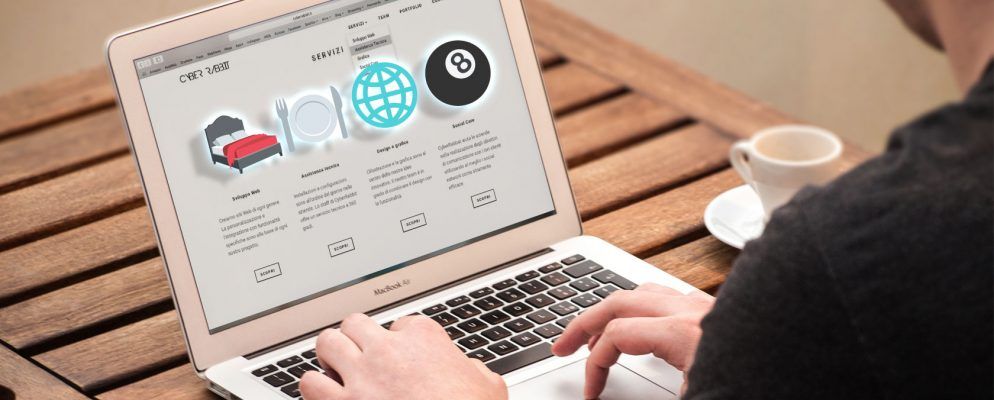
您听说过图标,并且几乎可以肯定听说过字体,但是图标字体是什么?今天,我将向您展示什么是图标字体,以及如何使用它们来激活您的网站。让我们开始吧。
什么是图标字体?
图标字体与“常规"字体完全相同-它们定义了一段文字的外观。这里最大的区别是图标字体不包含字母和数字,而是符号和图标。您可能对此感到困惑,因为如果您不能给妈妈写信的话,字体有什么用!
图标字体主要用于设计网站样式。由于它们是基于矢量的,因此可以使用CSS对其进行大小调整,移动,样式设置和更改。与传统的设计方法(例如图像)相比,这提供了巨大的优势。只需几行代码,即可更改大量图标的外观。您无需编辑任何图像,打开Photoshop或上传新文件,只需编写代码即可。
入门
在这些示例中,我将使用Font Awesome ,但该理论也可以应用于许多其他字体包。
以下是入门HTML:
<!DOCTYPE html><html> <head> <meta charset="UTF-8"> <title>MUO Icon Fonts</title> <link rel="stylesheet" type="text/css" href="https://maxcdn.bootstrapcdn.com/font-awesome/4.7.0/css/font-awesome.min.css"> <style> html { font-family: helvetica, arial; } </style> </head> <body> </body></html>这是生成网页所需的最少HTML量。我不会解释其中的大部分内容,因为我们已在指南中介绍了如何制作网站。
最重要的一行如下:
<link rel="stylesheet" type="text/css" href="https://maxcdn.bootstrapcdn.com/font-awesome/4.7.0/css/font-awesome.min.css">这将从其CDN加载Font Awesome样式表。没有这一行,您的网站将不知道什么是Font Awesome,因此它非常重要。该样式表处理了嵌入Web字体的所有艰苦工作,并且通常使您更轻松。
字体真棒图标由添加到 i 标签的CSS类定义。选择这些图标是因为它们未附加任何浏览器或默认定义的样式,因此您的图标不会一团糟。另外,您可以将类添加到 span 标签,但这会使HTML变得混乱。
这是基本用法。将其放在您的 body 标签中:
<i class="fa fa-cog"></i> My First Icon这是下面的样子:
那有多容易?让我们分解一下。要使用Font Awesome,需要两个类。第一个叫做 fa ,代表Font Awesome。无论使用哪种图标,任何图标都需要此图标。第二类指定您希望使用的特定图标-它可以是任何东西,飞机,人或信用卡。它也以 fa 为前缀,并且由于它是齿轮图标,因此名称为 fa-cog 。您可以在其网站上查看Font Awesome中所有图标的列表。
尝试将图标从齿轮更改为其他图标。
更深入
一旦您了解了基础知识,就该使用一些高级技巧了。
如果您不想编写自己的CSS,则可以使用Font Awesome内置的样式。您可以使用许多类来放大图标:
另一个有用的类是 fa-spin 。这将使您的图标旋转,并且与以前的尺寸类别组合时,您可以产生一些不错的效果。代码如下:
旋转图标很容易-使用 fa-rotate 类:
<i class="fa fa-envelope-o fa-3x"></i><i class="fa fa-envelope-o fa-3x fa-rotate-90"></i><i class="fa fa-envelope-o fa-3x fa-rotate-180"></i><i class="fa fa-envelope-o fa-3x fa-rotate-270"></i>末尾的数字定义了图标的旋转角度,但是不要被带走。您只能使用 90 , 180 或 270 。
最后一个技巧就是堆叠。 fa-stack 类可让您将两个或更多图标组合在一起。这是代码:
一旦您开始组合所有这些不同的类,可能性就将是无穷无尽的。
自定义CSS
由于图标字体是 just 字体,因此可以像使用任何其他元素一样使用CSS设置样式。使用少量CSS3可以走很长一段路:
以下是该图标的HTML:
@keyframes move { from { margin-left: 0; } to { margin-left: 400px; }}.bike { animation-name: move; animation-duration: 4s;}此CSS非常基本,但影响很大。不过,这不是CSS教程,因此,如果您想进一步了解内部工作原理,则可能需要学习CSS。
如果您确实愿意,可以做一些特殊的事情:
为了减少Web的文件大小,这会有点结结巴巴。这是HTML:
@keyframes fade { from { opacity: 0; } to { opacity: 1; }}.person { opacity: 0; animation-name: fade;}#p1 { color: red; animation-duration: 2s;}#p2 { color: orange; animation-duration: 4s;}#p3 { color: green; animation-duration: 6s;}#p4 { animation-duration: 8s;}与前面的示例一样,它使用CSS3动画。创建了一个名为 fade 的动画,并且每个人形图标均以不同的时间实现该动画。这些图标和CSS3潜力巨大。